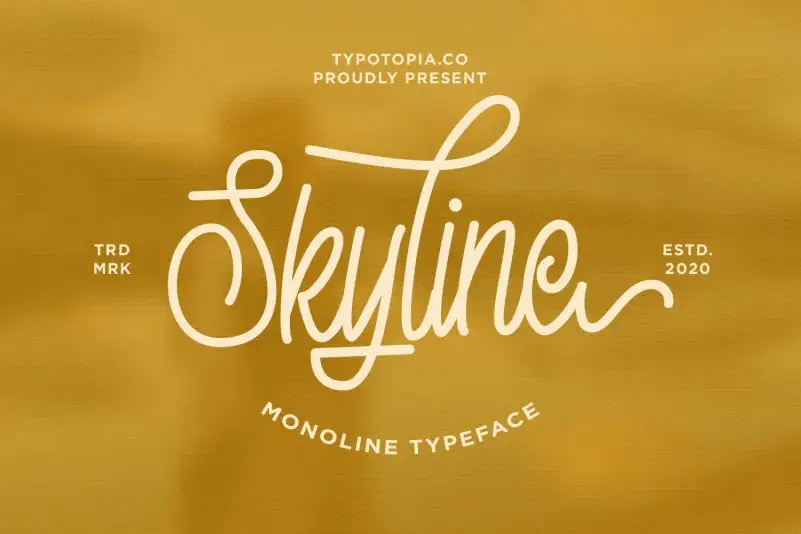
Skyline Monoline Script Font – Download Grátis
A fonte Skyline Monoline Script é perfeita para projetistas que buscam uma tipografia script elegante e única. Ela foi criada especificamente para seus próximos projetos de design, como logos, cartões, embalagens, cabeçalhos, logotipos, carta, painéis ou até mesmo roupas personalizadas. O designer typotopia nos oferece esta fonte monoline que traz uma dinâmica especial aos seus trabalhos. Ideal tanto para aplicar em um projeto de identidade visual como para criar arte digital atraente e única. Seja ela o destaque em seu próximo banner, ou simplesmente aquele detalhe adicional em suas letras digitais — Skyline Monoline Script traz uma paleta vibrante de opções à sua disposição. Englobe todos estes cenários com esta fonte e transforme seus projetos no ponto de encontro perfeito entre criatividade e design, criando um impacto visual imediatamente reconhecível em seu trabalho.